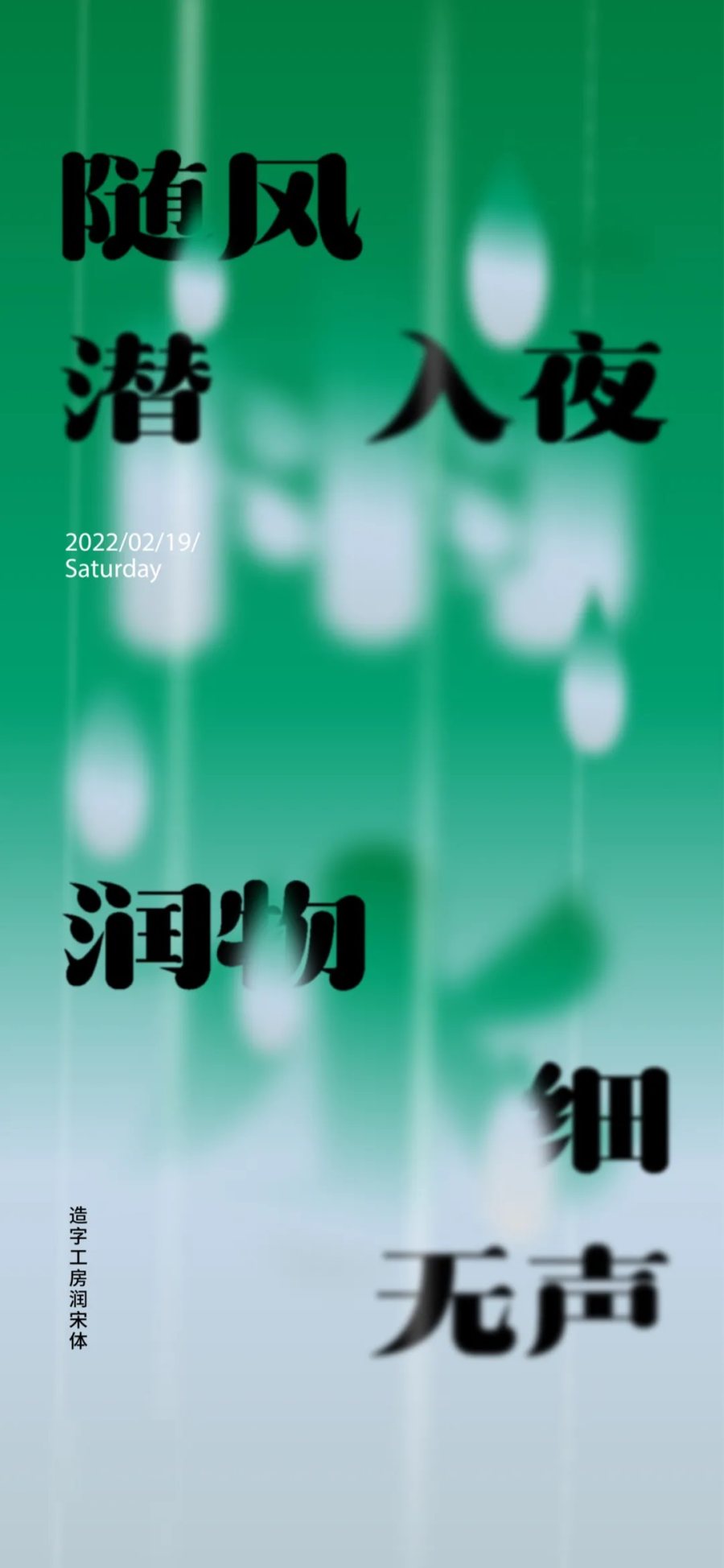
造字工房润宋体,其字体遒劲润雅,结字工巧、奇宕潇洒,笔画粗劲圆润、浑厚宽博。线条温润饱满,圆转藏锋、张力十足、风神超迈,具有很强的视觉感染力。本字体适用于各类商业广告、会刊杂志、个性品牌设计推广等环境。本字体为简体字库,采用OpenType/CID格式,Adobe-GB1-5编码。基于中华人民共和国GB2312-80字符集标准,另按需添加101个汉字。共收容字数6864CJK汉字,ASCII常用字符100个。